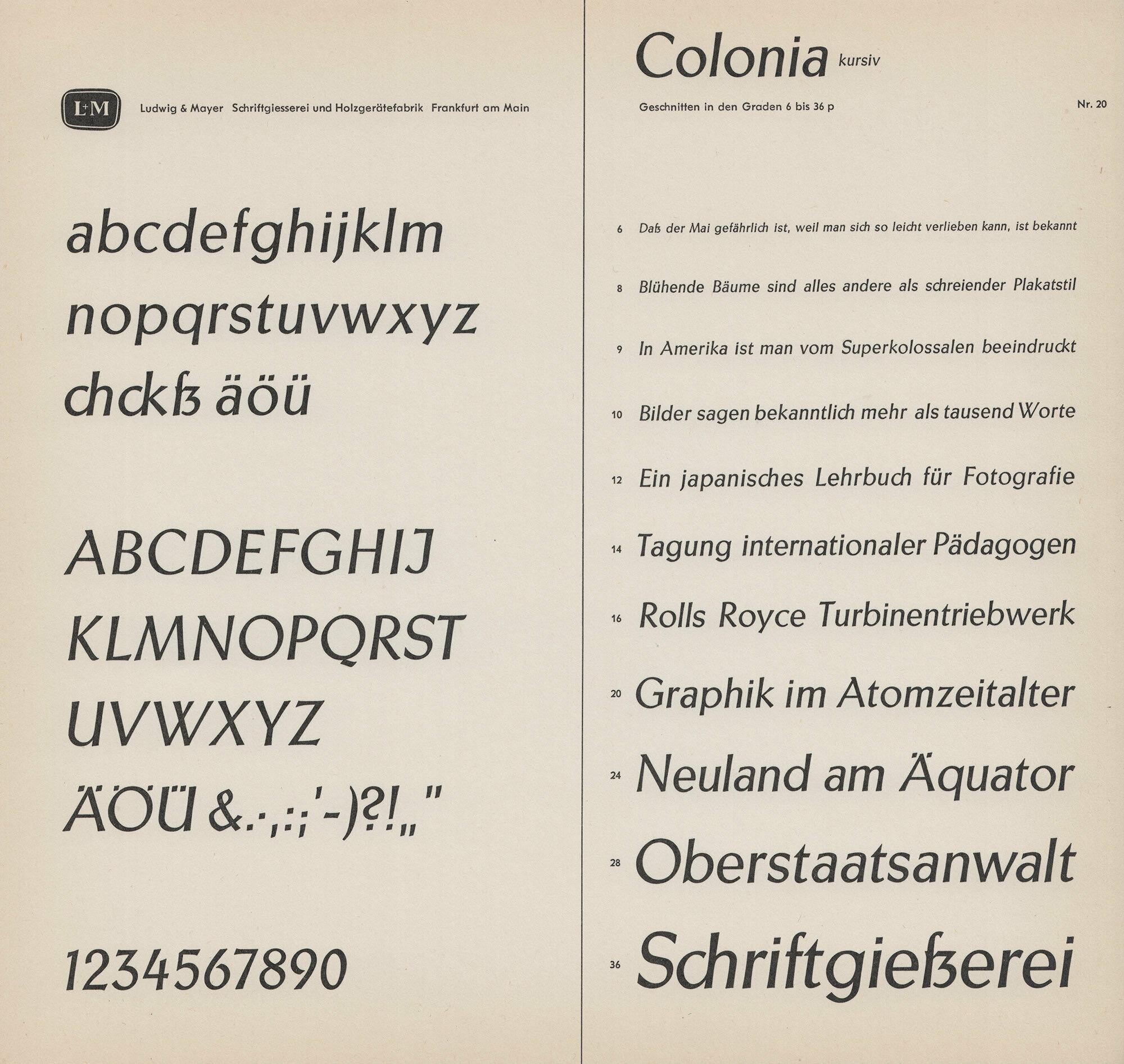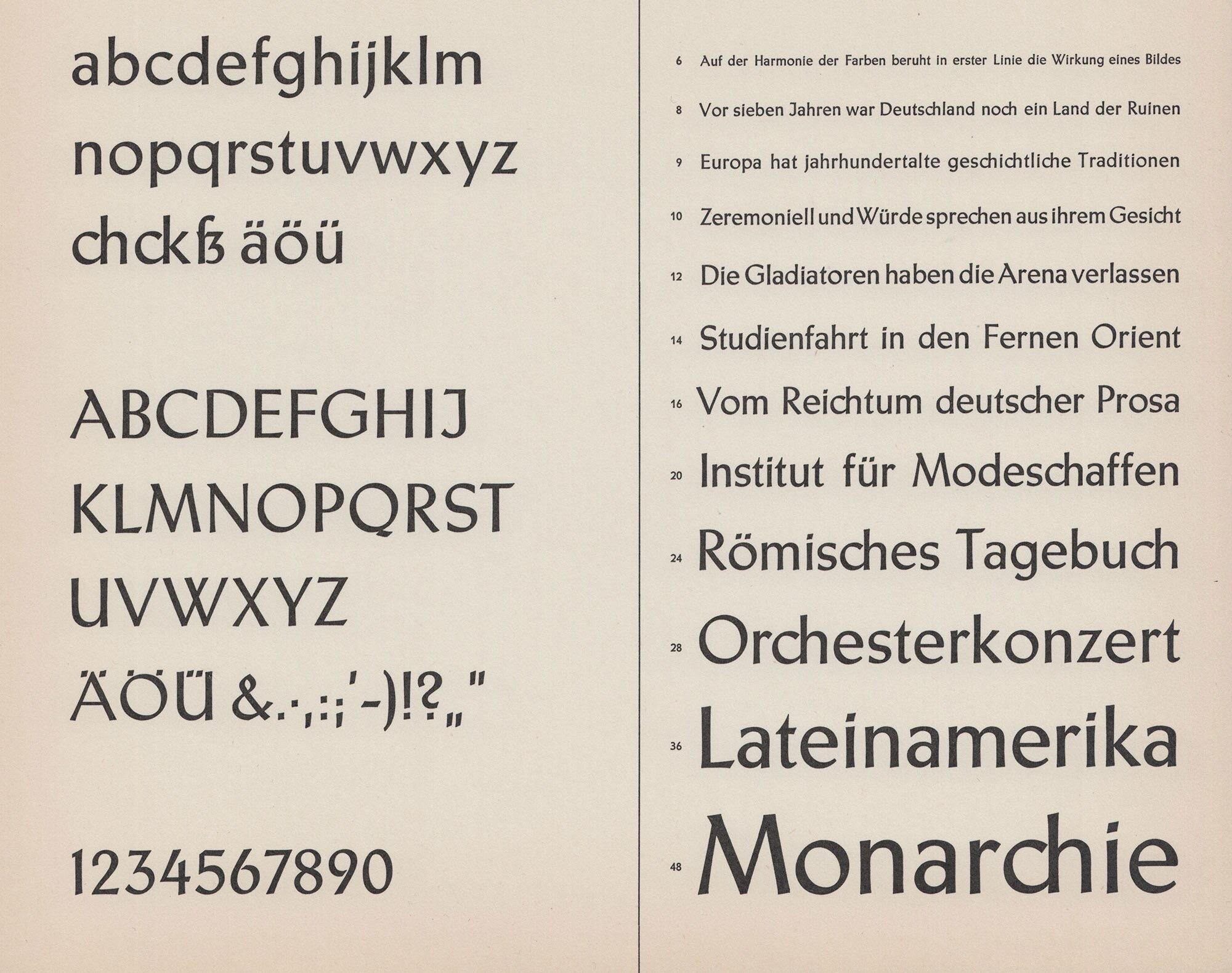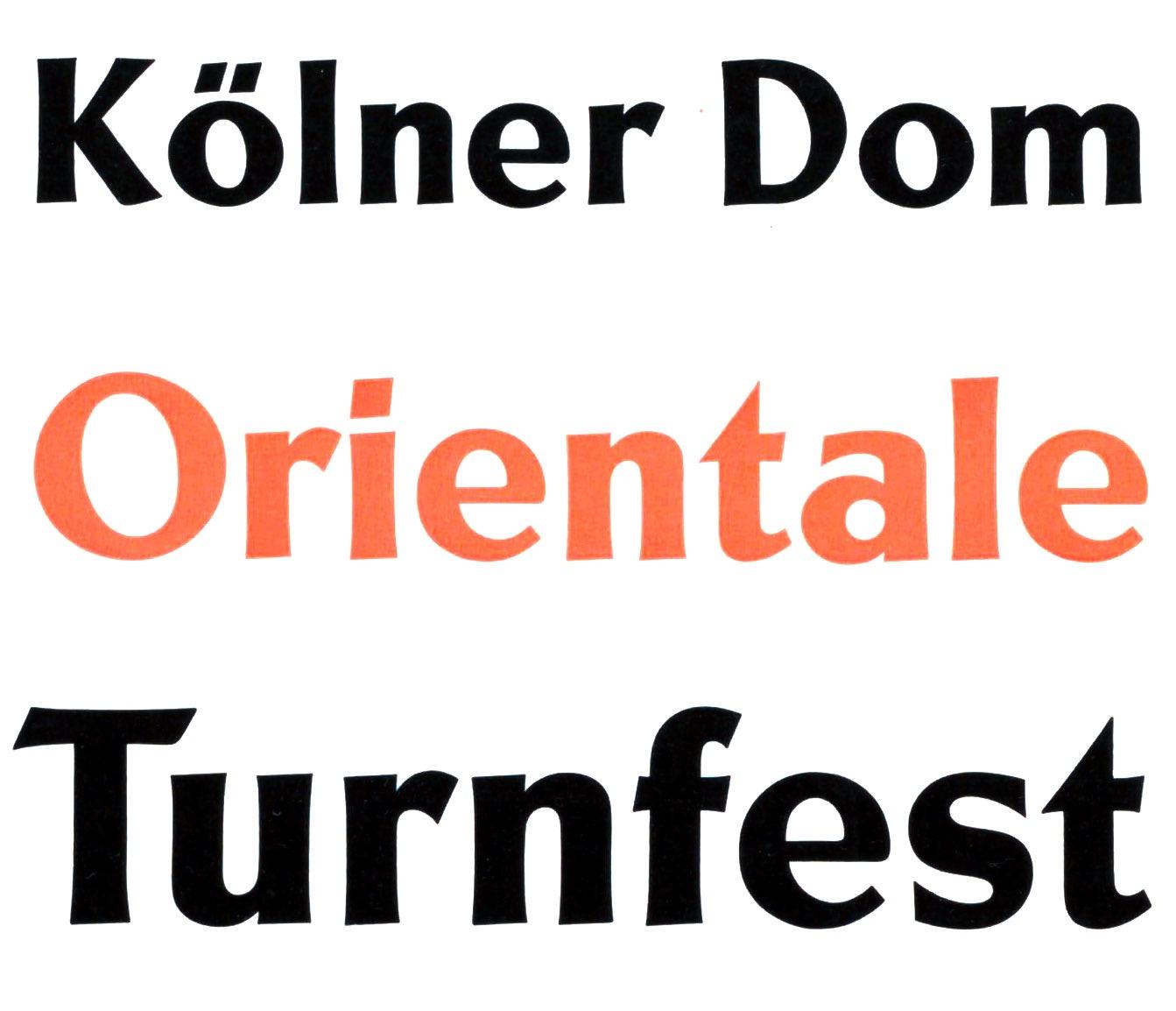
Font-Wiki: Colonia
Die Colonia ist eine Antiqua-Familie von Walter Ferdinand Kemper und erschien Ende der 1930er-Jahre bei der Gießerei Ludwig & Mayer. Die Familie bestand aus einem mageren, einen kursiven und einem fetten Schnitt.